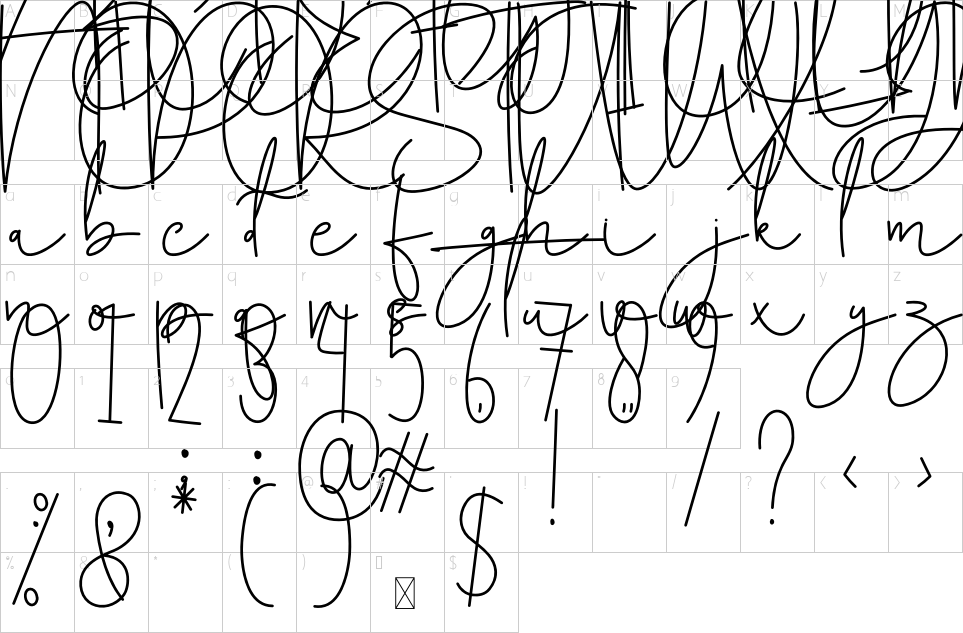
Autográfia é uma fonte moderna e elegante que chama a atenção por sua facilidade de uso e beleza gráfica. Desenvolvida pelo designer inédito scratchones, a Autográfia foi projetada para oferecer uma experiência gráfica agradável tanto para designers digitais quanto para os amantes do design. Com uma aparência minimalista e moderna, a fonte é ideal para textos e gráficos que precisam de um toque sofisticado e criativo. Seu design fluido permite que você personalize e adapte o texto, tornando-a uma ótima escolha para criações de e-commerce, design gráfico e para adicionar um toque único a qualquer projeto. Sua versatilidade e facilidade de uso fazem dela uma fonte gratuita excepcional que vale a pena ser experimentada.